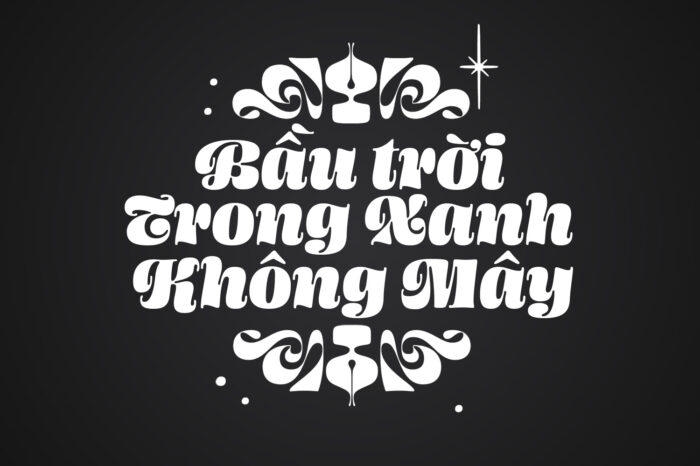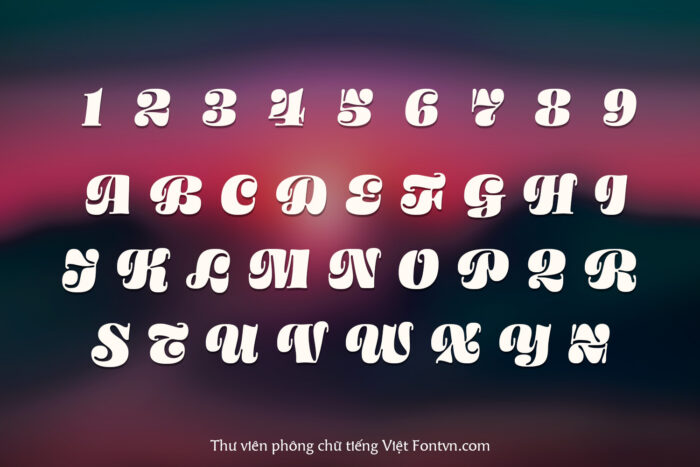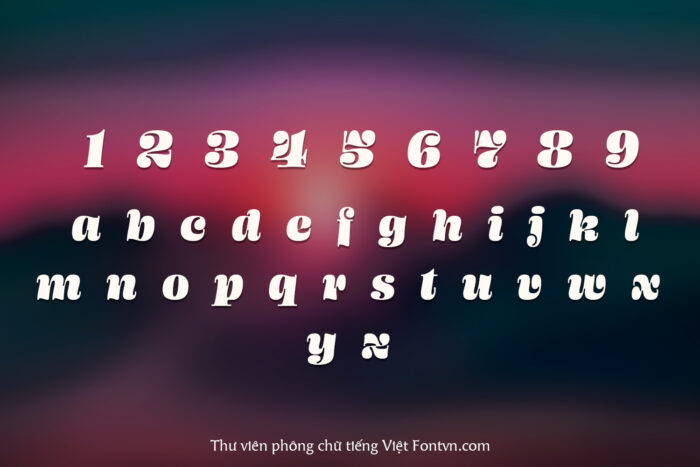
DVN Lively Việt hóa – Font chữ Script vui tươi thích hợp làm thiệp mời, typography
DVN Lively Việt hóa là một font chữ script mang phong cách vui tươi và năng động, được thiết kế với những đường nét mềm mại nhưng đầy đặn, tạo nên sự hài hòa giữa sự thanh lịch và nổi bật. Font chữ này đặc biệt ấn tượng với các ký tự tròn trịa, thể hiện sự sáng tạo và linh hoạt, phù hợp cho những thiết kế cần sự thu hút ngay từ cái nhìn đầu tiên.
DVN Lively Việt hóa hoàn toàn thích hợp cho việc làm thiệp mời đám cưới, các thiết kế trẻ em, vui tươi và năng động. Bên cạnh đó, font chữ này cũng lý tưởng để sử dụng trong các dự án typography, nơi cần sự phá cách nhưng vẫn giữ được tính thẩm mỹ cao. Với DVN Lively, mỗi thiết kế của bạn sẽ trở nên sống động hơn, tạo nên ấn tượng mạnh mẽ và khó quên cho người xem.